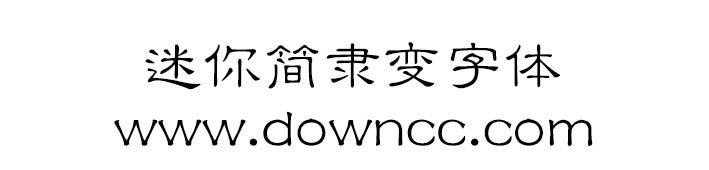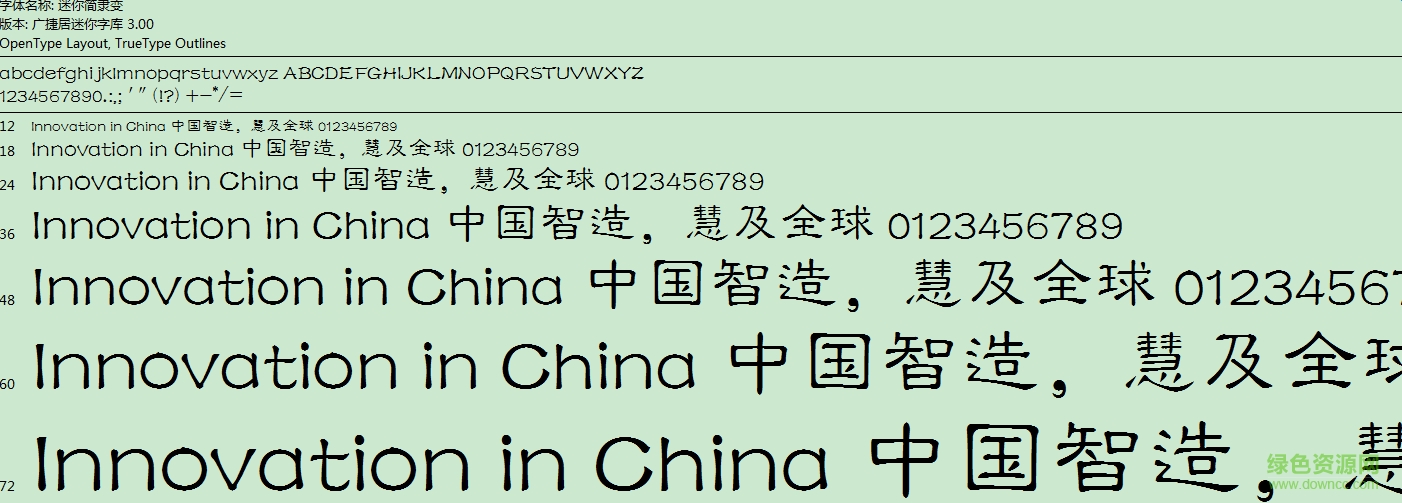
迷你簡(jiǎn)隸變是一款隸書字體的衍生字體版本,文字看起來生動(dòng)形象,富有趣味。適合作為藝術(shù)素材使用。小編為大家提供免費(fèi)下載地址,快來綠色資源網(wǎng)下載吧!
迷你簡(jiǎn)隸變是非常常用的一種字體,它還是有隸書的字形多呈寬扁,橫畫長而豎畫短,但是它又多了一種活潑的寫法,所以看起來是一種青春的感覺